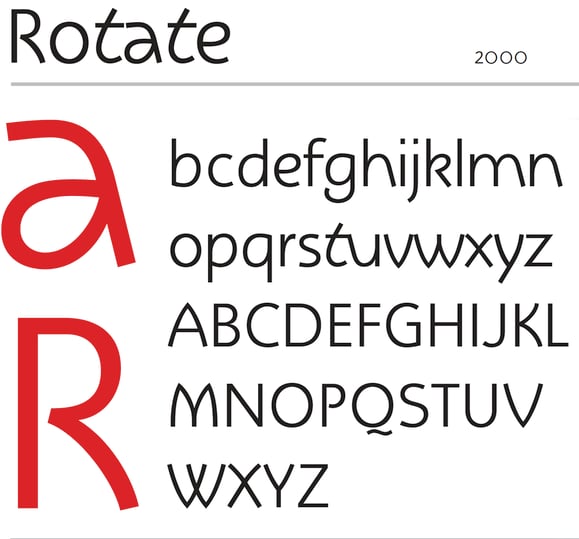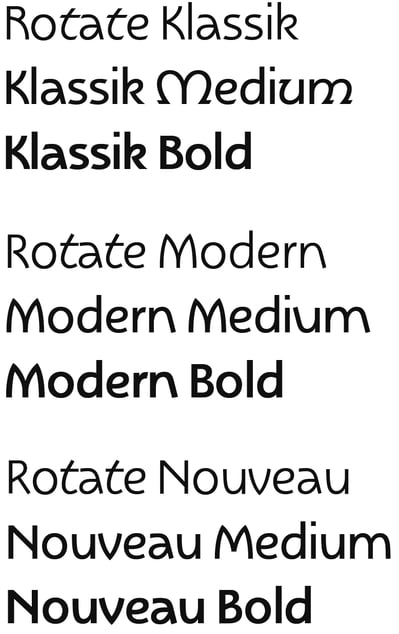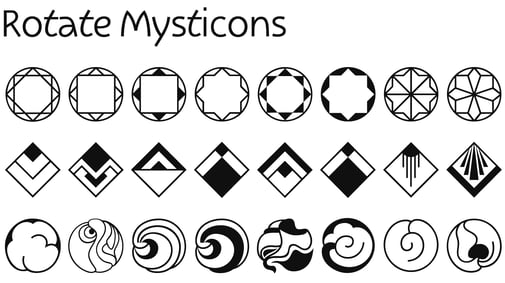
Rotate
Aus einem einzigen Zeichen – dem »a« – sind in diesem Fall drei verwandte Schriften entstanden. Zu diesem a versuchte ich ein passendes Alphabet zu machen. Dabei entstanden immer neue Varianten von einzelnen Buchstaben, die wieder zu Abwandlungen bei anderen Typen des Zeichensatzes führten. Jetzt besteht die »Rotate« aus drei verwandten Gruppen, die sich stilistisch der klassischen Unziale und Rotunda, dem Jugendstil und dem Art Deco zuordnen lassen. Dabei fügen sich teilweise identische Buchstaben in die unterschiedlichen Formprinzipien ein. Dazu passt der Symbol-Font »Mysticons« mit Mandala-, Jugendstil- und Art Deco-Elementen. Diese wurden zum Teil aus vorhandenen Skizzen und Projekten genommen, teils neu gestaltet in Anlehnung an typische Jugendstil- und Art- Deco-Designs.